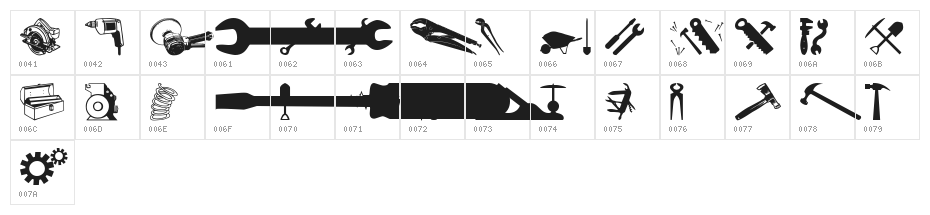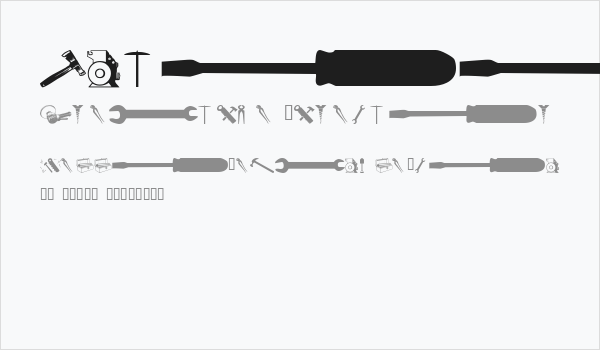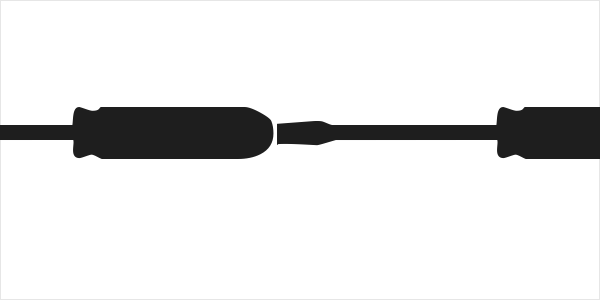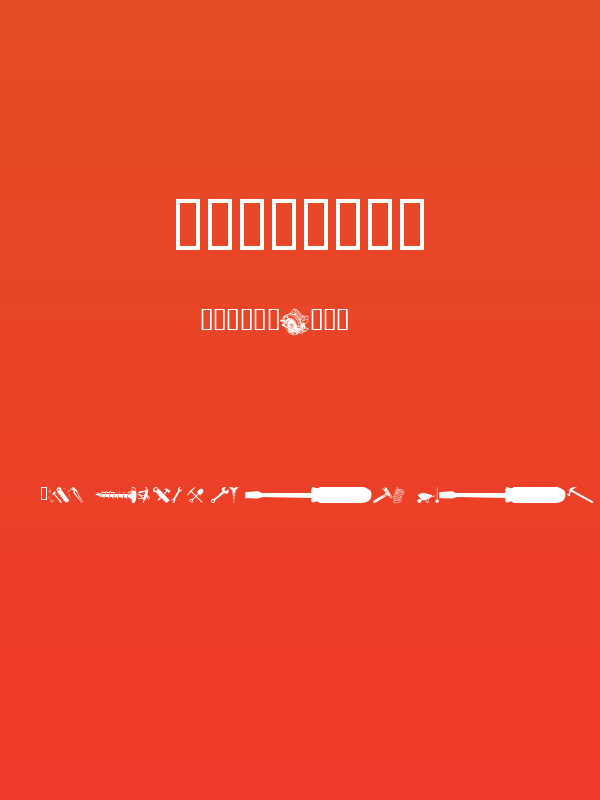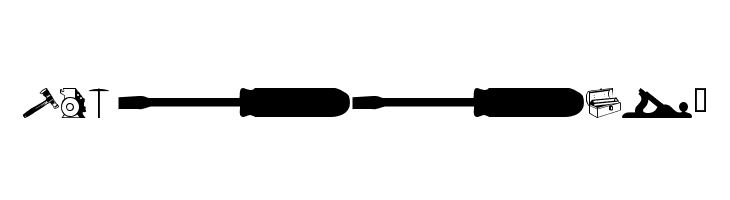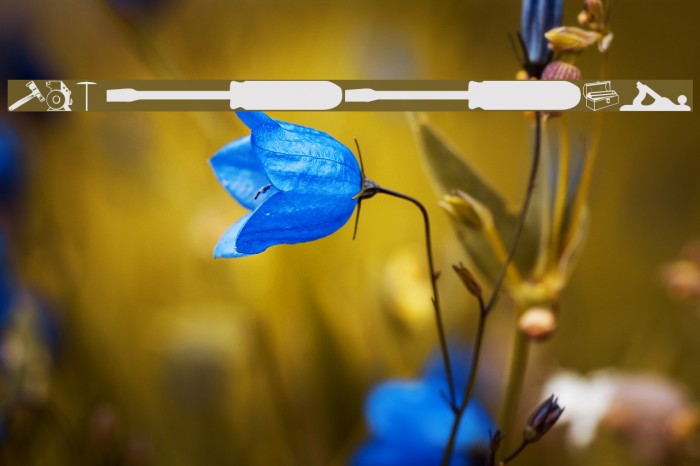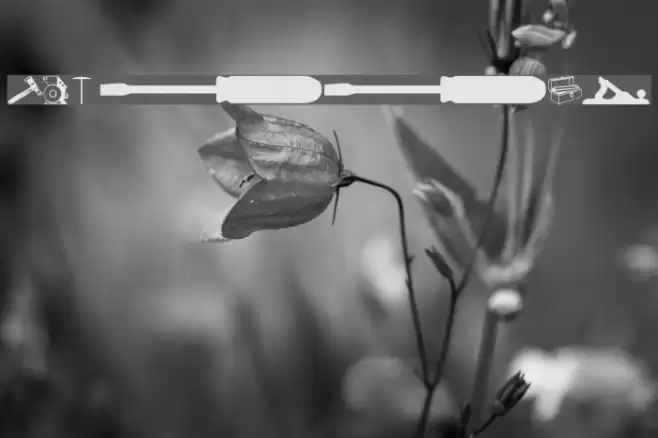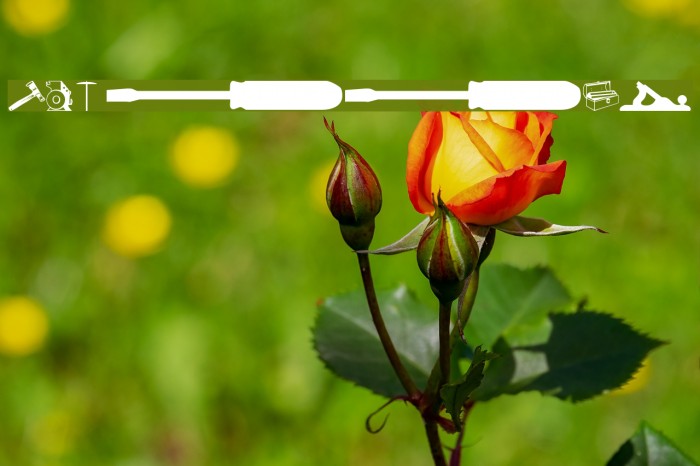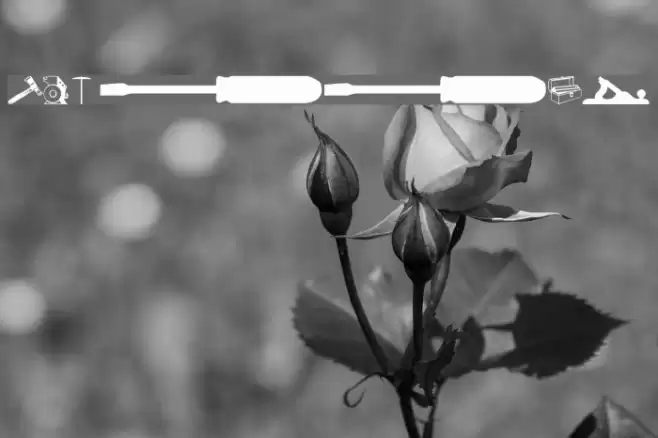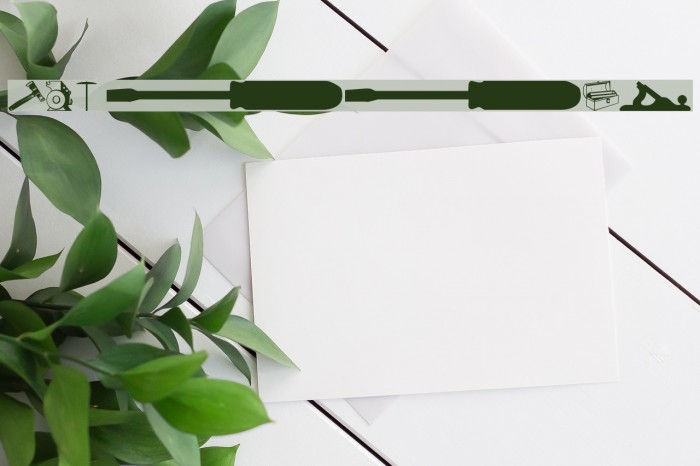
wmtools1 Font
✎ Dingbats
| 全体的なスタイル | Decorative, Thematic |
| 用途 | Icons, Themed graphics, Decorative headings |
| おすすめプロジェクト | DIY project flyers, hardware store signage, tool-related infographics, educational materials, themed invitations. |